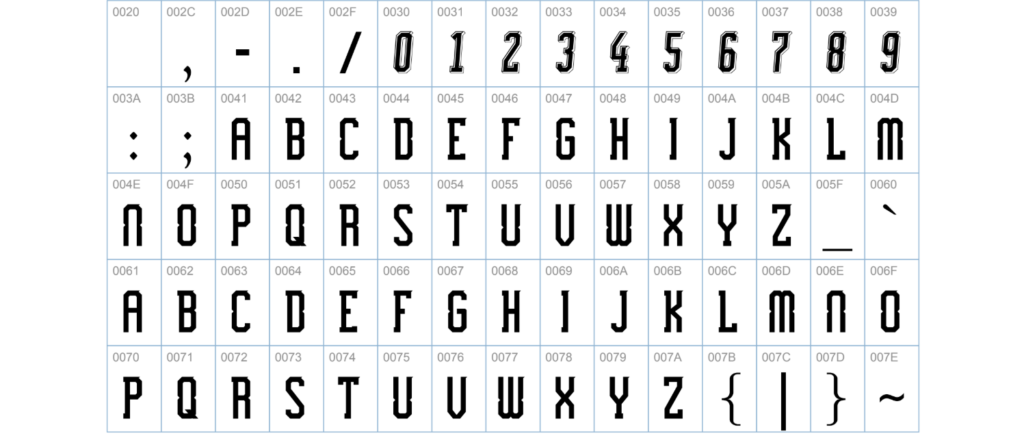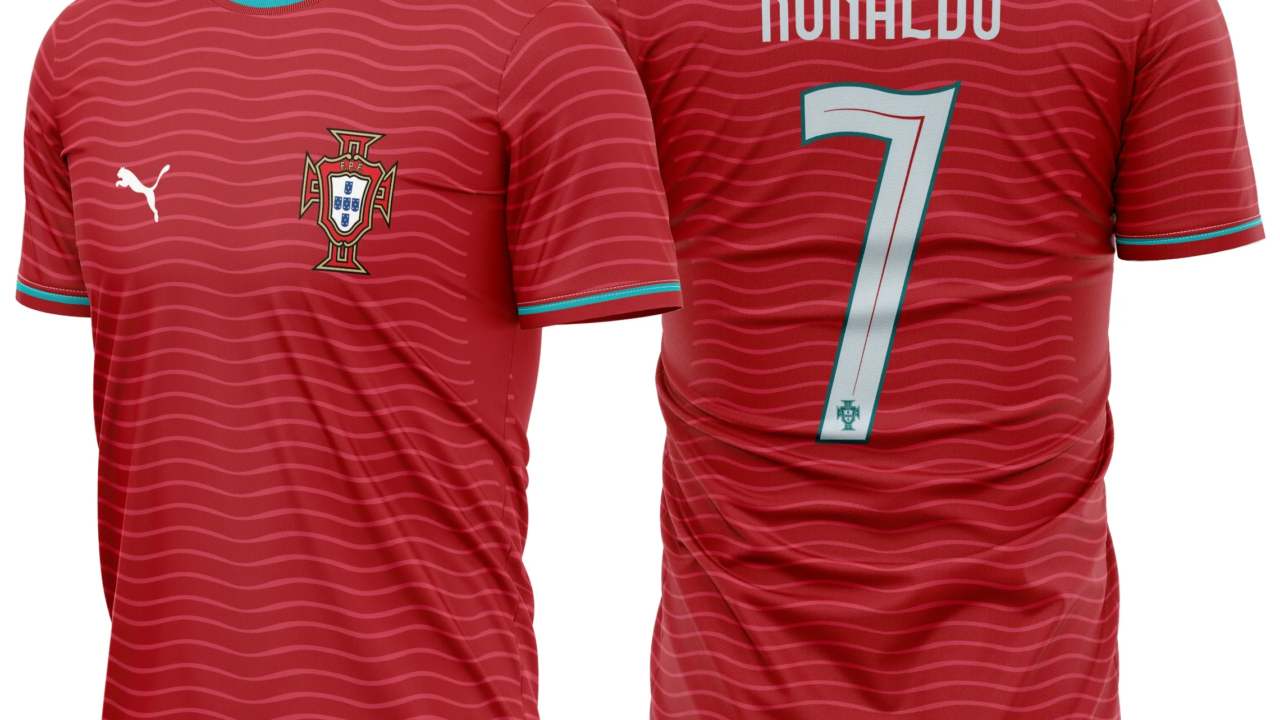
A Seleção Portuguesa entra em 2026 com um visual renovado, mirando a Copa do Mundo. Cada detalhe do novo uniforme foi pensado para unir tradição e modernidade — e a tipografia é a assinatura silenciosa dessa identidade.
A fonte oficial dos números e nomes carrega o peso da camisa lusitana. Ela traduz ambição, velocidade e a herança de um futebol que respira talento. Fãs, designers e colecionadores já procuram o arquivo para projetos pessoais, montagens e camisas personalizadas.
Estilo visual da tipografia
O desenho aposta em números com hastes retas, cantos levemente arredondados e um corte dinâmico que remete ao movimento em campo. O “7” ganha um traço firme e inclinado, enquanto o “10” preserva boa largura, garantindo leitura instantânea na transmissão de TV. É uma fonte moderna, mas sem abandonar a elegância clássica que a camisa de Portugal exige.
Aplicação no uniforme
No Home (titular), a fonte aparece em dourado sobre o tradicional vermelho, criando contraste nobre. No Away (reserva), o branco assume os números com um filete rubro, mantendo a identidade. A camisa Third traz a tipografia em tom metálico discreto, ideal para jogos noturnos e coleções especiais.